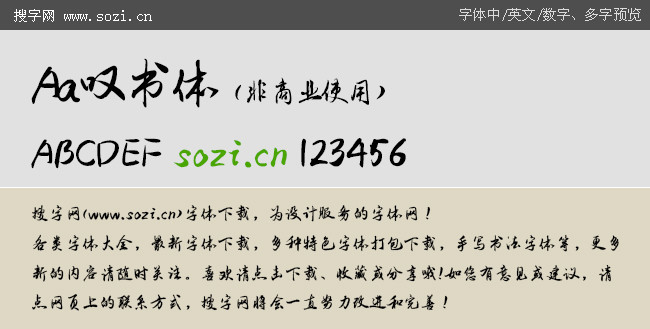
Aa嘆書體(非商業(yè)使用)
搜字網(wǎng)給大家提供一款A(yù)a嘆書體(非商業(yè)使用)中文字體下載,該字體是一款手寫中文字體,這款字體筆觸粗細(xì)適中,字形端莊,書寫靈動(dòng)飄逸,適合包裝設(shè)計(jì)、書裝設(shè)計(jì)、海報(bào)設(shè)計(jì)等應(yīng)用(此字體為個(gè)人非商用版,商用可以聯(lián)系QQ:1006760504)。